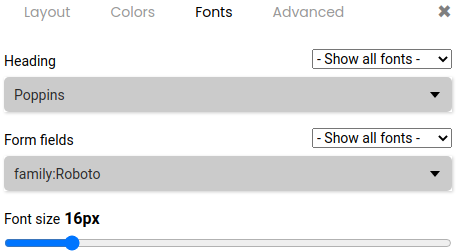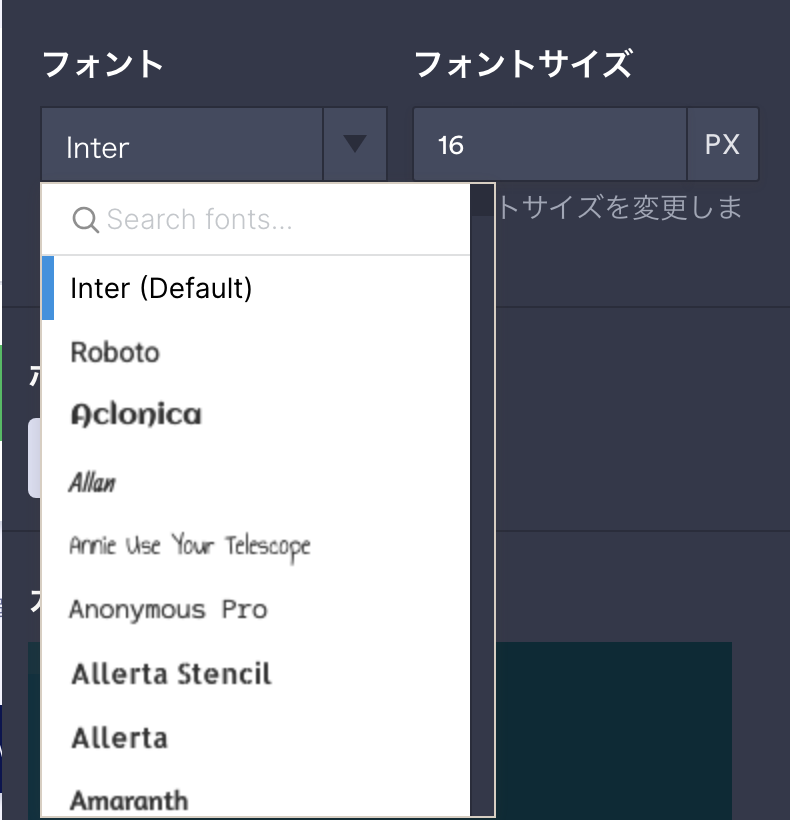
Googleフォームはシンプルなツールです。もともとはGoogleスプレッドシートのアドオンとして設計されたものですが、2016年に独立したアプリとなりました。
Googleフォームは時間をかけて新機能を組み込んできてはいるものの、提供される機能は、限られています。Googleはフォームなどのツールよりも、スプレッドシートやドキュメントのような主力製品に力を入れているのです。
ですから、Googleフォームではフォントサイズを変更することはできますが、期待するほどのものは備わっていないかもしれません。しかし、この記事を参考にすれば、フォント変更の選択肢は限られているものの、いくつかのアドオンと、より多くの選択肢を与えてくれる回避策があることがわかるはずです。
既存機能でフォントを変更する
Googleフォームには、フォームをカスタマイズしたりデザインしたりするためのオプションがいくつか用意されています。
すべてのデザイン設定は1箇所にまとめられており、フォントを決めた後も、さまざまなデザインを調整することができます。
これらの設定を行うには、右上隅にあるパレットのアイコンをクリックすしましょう。
すると、ページの右側にテーマ・オプションのメニューが開きます。フォントスタイルはリストの一番下です。以下の画像で一例が確認できますが、ここでは驚くほどたくさんのフォントを選ぶことができます。
豊富な選択肢に圧倒されないようにしましょう。フォントには、一般的なセリフ体フォントと一般的なサンセリフ体フォントがあり、どちらも十分です。Comic Sansというフォントに似ているPlayfulもあります。そして、20歳未満の人には読めないDecorativeも備わっています。
アドオンを使う
より多くのフォントを手に入れるための最良の方法は、アドオンを使うことです。ただし残念なことに、フォントに関するアドオンで利用できるのは1つに限られており、これを使用すると、Googleフォームのスタイル設定は完全に削除されます。
このアドオンはFormfacadeと呼ばれています。これは有料のツールで、Googleフォームを独自のブランディングでウェブページに埋め込むことを可能にします。
Formfacadeは、フォームのデザイン設定という点に関しては十分な機能を備えていますが、それ以上の機能は備わっていません。Google フォームの上に配置され、見た目を少し美しくするだけです。
すると、Formfacadeのウェブサイトに遷移し、そこでフォームのデザインを編集できます。フォントを変更するには、フォームのタイトルの横にある歯車をクリックしてください。
右側の設定メニューから、Fontsタブを選択します。
最善の方法:他のツールを使用する
冒頭で述べたように、Googleフォームはとてもシンプルなツールです。ここまで読んで来た方は、おそらく上記のアドオンを使うという選択肢には満足していないのではないでしょうか。では、他に何ができるのでしょう?
時には、諦めるのが一番良い選択肢です。もちろんこれは、フォームを作ることを諦めるという意味ではありません。しかし、Googleフォームを使用することを、諦めることも考えてみましょう。フォント数は、Googleフォームの制限のほんの一部にすぎず、Googleフォームには他にもさまざまな制限が存在しています。
しかし、フォントについてはどうでしょうか?実はJotformにはたくさんのフォントが組み込まれています。そして、フォント選択も簡単です。
もしあなたに特別にこだわりがあって、このフォントリストの中に気に入ったものが見つからなかった場合はどうすれば良いのでしょうか?そういった場合は、フォームに直接CSSを挿入したり、どこからでもフォントをインポートしたりすることが可能です。高度なフォームデザイナーを使用して、レイアウトのあらゆる側面を調整することもできます。